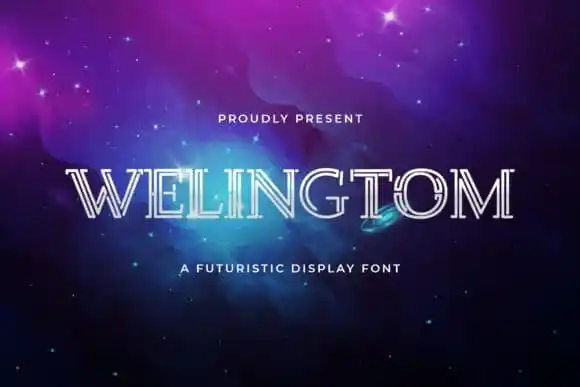
A fonte Welingtom Display é uma seleção elegante para designers amantes do modernismo e da delicadeza. Com seus caracteres bem balanceados e suaves, essa fonte é perfeita para criar designs que se destacam, tendo em vista seu uso em um vasto conjunto de projetos. Ela foi criada pelo StringLabs, uma equipe proeminente no design de fontes, resultando numa tipografia autêntica e futurista. Suas linhas fluidas e agradáveis aos olhos fazem dela uma escolha ótima para impulsionar suas ideias criativas ao nível mais alto. Sem dúvidas, ela trará um toque de elegância e originalidade a cada projeto que você criar utilizando essa fonte Welingtom Display.